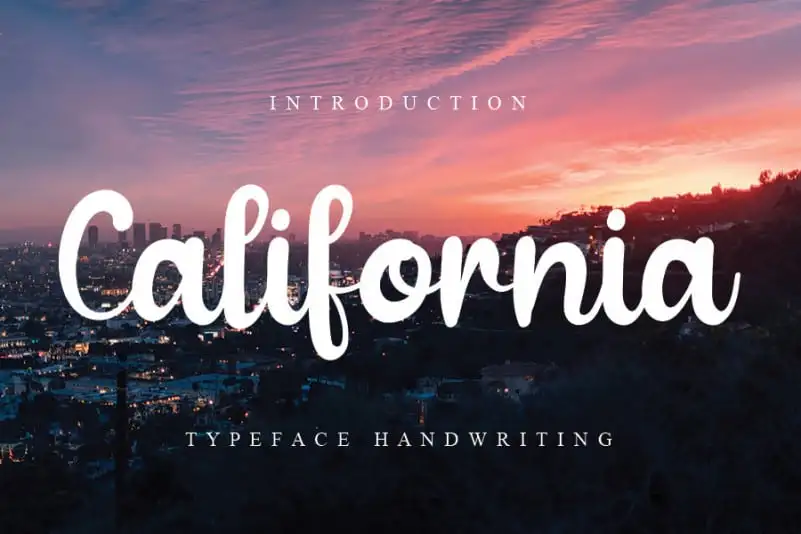
A fonte ‘California Font’ é ideal para quem busca um script elegante e expressivo. Esta opção especial vem da equipe da Andikastudio, designer que entende perfeitamente a delicada harmonia entre formas levemente fluidas e estilos característicos, criando uma experiência visual única. Utilizando ‘California Font’, seus projetos ganharão um toque de sofisticação, adaptável para diversos usos como cartazes urbanos, design editorial ou até mesmo gráficos pessoais. Com uma linguagem suave que se destaca da multidão, esta fonte é perfeita para transmitir emoções e sentimentos em qualquer projeto digital ou impresso que você encarregue. Descubra a versatilidade desta fonte e deixe seu trabalho expressar um pouco mais de si mesmo com ‘California Font’.